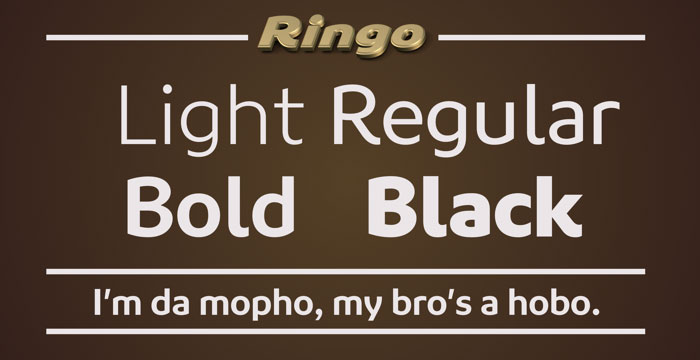
Die Ringo ist eine Schriftfamilie des polnischen Schriftgestalters Łukasz Dziedzic. Momentan ist die Familie in 4 Strichstärken mit je 580 Glyphen ausgebaut.
Als Besonderheit gibt es die Ringo unter dem Namen Ringo Blingo auch als kostenlose farbige 3D-Schrift.